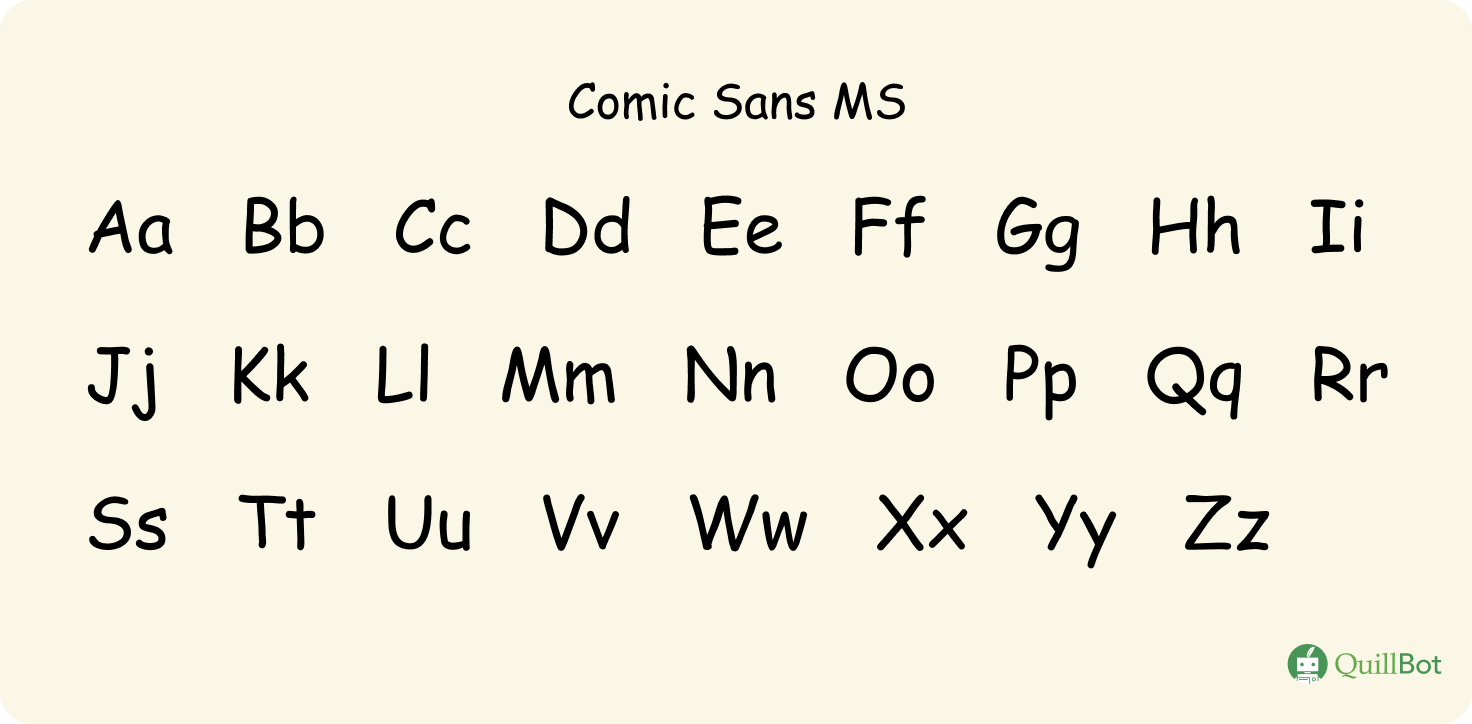
Comic Sans | Origen, características y usos
Comic Sans es una de las tipografías más célebres (y quizás una de las más controvertidas) a nivel global.
Comic Sans fue diseñada por Vincent Connare en 1994 con el propósito de ofrecer una tipografía informal y legible, especialmente pensada para materiales didácticos y el público más joven.
La tipografía Comic Sans es una de las más recomendadas para personas con dislexia, ya que sus caracteres tienen formas irregulares y distintas entre sí, lo que permite distinguir con facilidad letras similares como “b” y “d” o “p” y “q”, que en otras tipografías pueden llegar a confundirse.
Hoy día, Comic Sans también es muy usada en otros contextos informales, como cartelería artesanal en comercios locales, felicitaciones de cumpleaños e incluso contenido digital como memes.
Comic Sans: origen y contexto histórico
Comic Sans fue creada en 1994 por el diseñador de Microsoft, Vincent Connare, para un software interactivo infantil llamado Microsoft Bob (un perro de dibujos animados).
El nombre oficial de la tipografía de Comic Sans es Comic Sans MS, donde “MS” hace referencia a Microsoft.
El objetivo era ofrecer una tipografía alternativa, más informal que Times New Roman o Arial, para un público más joven.
Para ello se inspiró en los globos de diálogo de cómics, como Batman y Watchmen.
En 1995, Microsoft decidió que Comic Sans formara parte de las fuentes de Windows 95, lo que disparó su uso masivo. Es aquí donde reside el rechazo de los diseñadores a Comic Sans: el problema no era la tipografía en sí, sino el uso inapropiado por parte de los usuarios.
Por ello, es clave entender cómo y en qué contexto es adecuado utilizar una letra como Comic Sans, ya que el éxito de un mensaje no solo depende del contenido, sino de que su forma y contexto sean coherentes con la autoridad de lo que se comunica.
Dan Gilbert, el propietario del equipo, emitió un comunicado oficial lleno de furia y promesas de venganza.
La seriedad y el peso emocional del mensaje se perdieron por completo al estar escrito en su totalidad con la tipografía Comic Sans.
La elección tipográfica de Comic Sans fue objeto de burla por parte de los medios de comunicación, quienes la tacharon de “infantil” y “poco profesional”.
Características principales de Comic Sans
Comic Sans es una tipografía sans serif (sin remates), caracterizada por su estilo informal, imitando el rotulado a mano de los cómics a través de trazos de grosor variable y una ligera inclinación.
A diferencia de otras tipografías sans serif como Helvetica, Comic Sans se distingue por sus caracteres con formas irregulares. Un ejemplo claro es la falta de simetría en letras como la “b” y la “d”.
Además, Comic Sans presenta una altura de x relativamente alta y un espaciado amplio entre caracteres, lo que contribuye a mejorar su legibilidad en tamaños reducidos.
Su diseño facilita la distinción de letras, siendo especialmente eficaz para personas con dislexia o en la etapa de alfabetización.
A diferencia de tipografías similares como Arial o Helvetica, donde la “I” es un simple trazo vertical que se confunde fácilmente con la “l” minúscula o el número “1”, Comic Sans incluye serifas (pequeños trazos horizontales) superiores e inferiores.
Usos y aplicaciones de Comic Sans
Comic Sans es una tipografía que, a pesar de ser tan controvertida, resulta adecuada en determinados contextos.
Algunos de los usos y aplicaciones más habituales de la tipografía Comic Sans son:
- Entornos educativos: Comic Sans es una elección acertada para proyectos de aula, materiales escolares, fichas de actividades, carteles, cuentos infantiles y otros recursos didácticos. Su diseño facilita la comprensión en trabajos colaborativos y presentaciones escolares.
- Comunicación informal: la tipografía Comic Sans también es común en contextos informales, como invitaciones a cumpleaños, señalización no oficial o memes, donde se busca transmitir cercanía sin formalismos.
- Accesibilidad: algunas organizaciones, como la Asociación Británica de la Dislexia, recomiendan el uso de Comic Sans para mejorar la legibilidad, ya que sus caracteres irregulares y diferenciados pueden reducir la confusión visual.
A pesar de la magnitud científica del evento —uno de los mayores hitos del siglo XXI—, la física Fabiola Gianotti presentó los datos utilizando la tipografía Comic Sans.
El contraste entre este hallazgo científico y la estética informal e infantil de la tipografía Comic Sans provocó una ola de críticas en las redes sociales y la comunidad científica.
Asimismo, Comic Sans no es apta para señalética, textos extensos o comunicaciones de temas sensibles.
Tampoco se aconseja emplear esta tipografía en entornos profesionales serios, como, por ejemplo, a la hora de redactar una carta de renuncia voluntaria. En este tipo de contextos, Quillbot te puede ayudar a escribir una carta de renuncia.
- Comic Neue: es una versión mejorada de Comic Sans, con trazos refinados que le dan un aspecto más profesional y equilibrado.
- Chalkboard: es la alternativa estándar de Apple. Es una tipografía muy utilizada en entornos educativos, con un diseño que recuerda a la escritura a mano pero con un acabado más pulido.
- Patrick Hand: es una tipografía inspirada en la caligrafía natural, ofreciendo un aspecto informal pero más limpio.